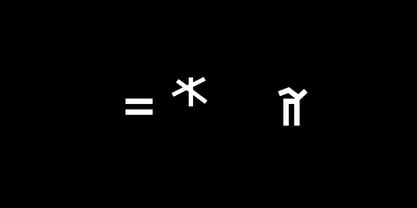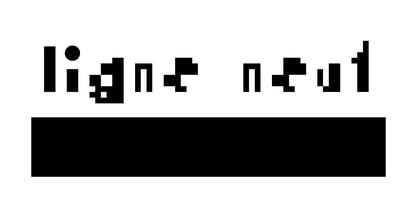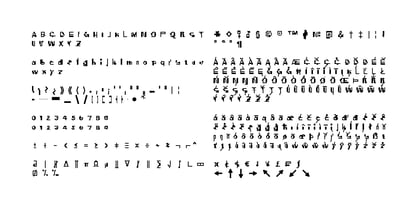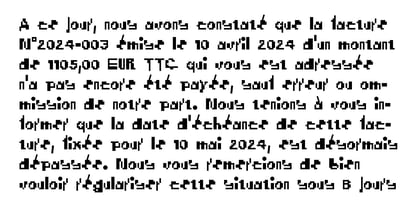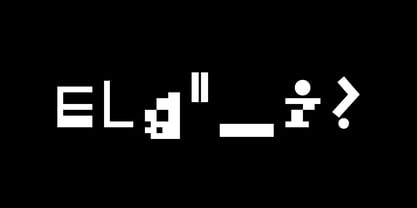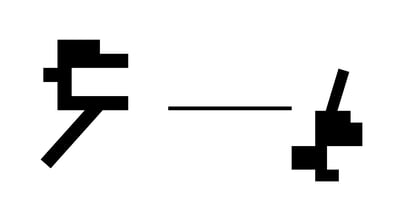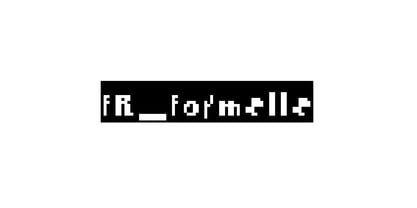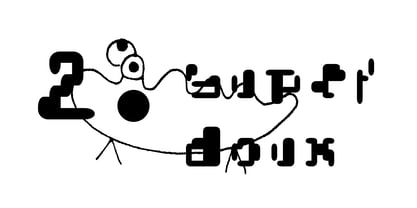
FR Formelle
by Luis Rutz
The FR Formelle Font Family was designed by Luis Rutz and published by Luis Rutz. FR Formelle contains 2 styles and family package options.
Die neue Französische! Für alle lateinischen Schriftsysteme. Verfügbar in eckig und rund.